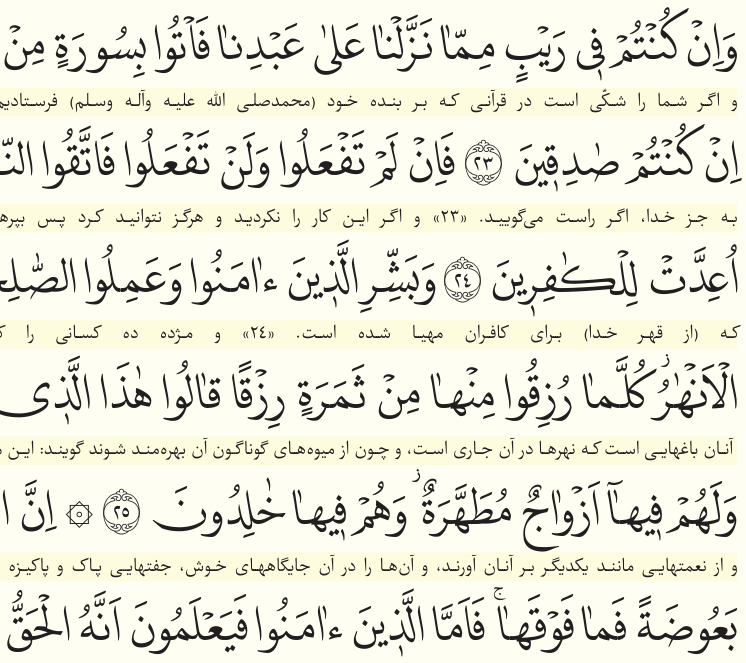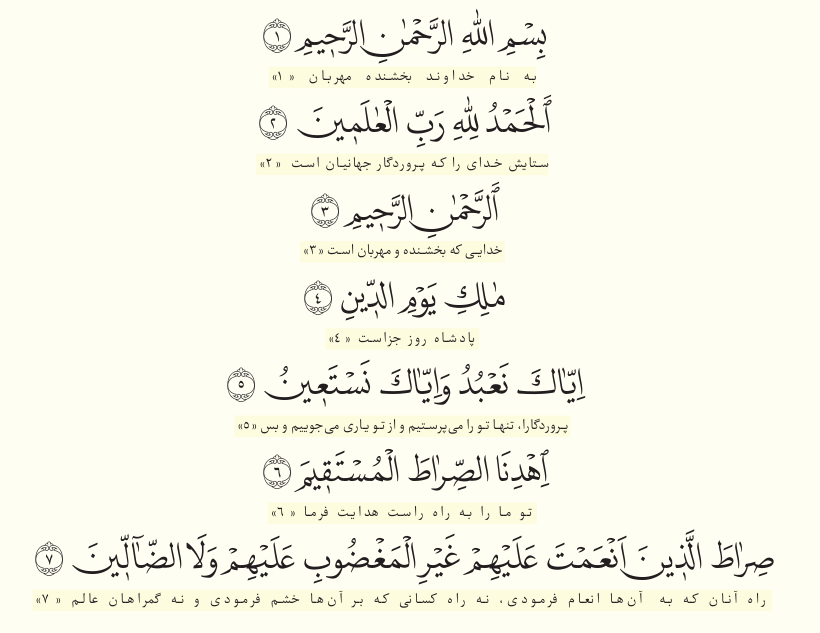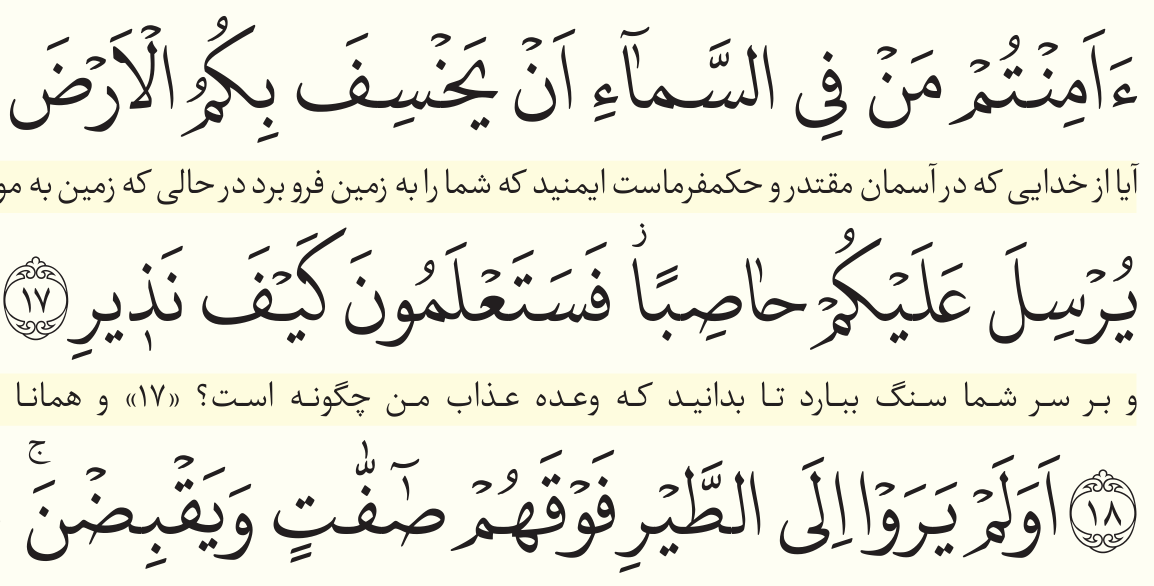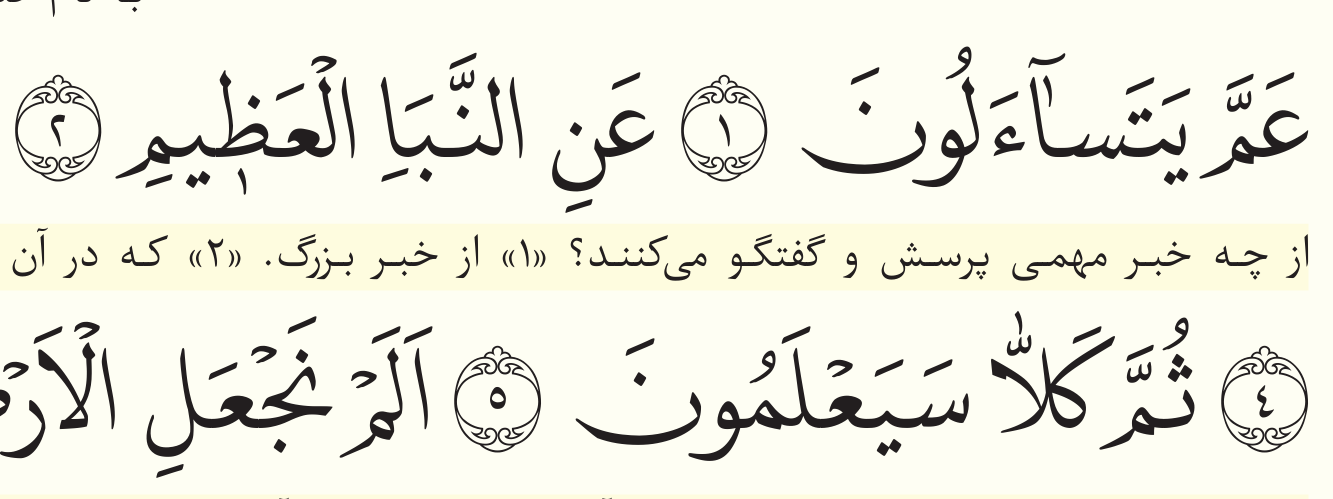
wm_Nabi Qurani
درباره قلم نبی قرآنی
حروف این قلم از قرآنهای چاپ جدید سعودی استخراج شده است. خطاط این قلم عثمان طه است. طراح محترم چند سال پیش، این قلم را با نام نبی بصورت رایگان در اینترنت منتشر کردند. با توجه به کاربرد قرآنی این قلم و ساختار هنری آن، نیاز به تایپوگرافی و مرتب سازی اعراب امری ضروری است لذا نسخه برتر آن میتواند نیازهای حرفهای کاربران را برآورده سازد..